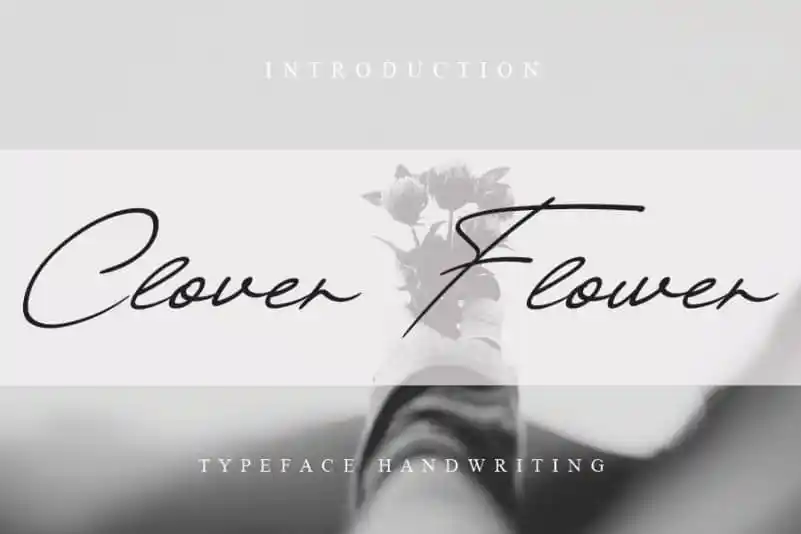
Clover Flower Handwritten Font – Download Grátis
A fonte ‘Clover Flower Handwritten Font’ é uma delícia para os olhos, sua textura suave e macia criando uma atmosfera harmoniosa e familiar. Perfeita para designers que valorizam elegância sem deixar de lado a simplicidade exuberante da escrita cursiva, esta fonte revigora qualquer projeto gráfico ao elevá-lo a um patamar inabalável de sofisticação e graça natural. Seja para criações de blogs pessoais, publicações online ou até mesmo para ilustrações em estilo vintage, ‘Clover Flower Handwritten Font’ é a escolha perfeita para aquelas pessoas que apreciam uma fonte que traz um toque suave e encantador ao seu trabalho. Seja você designer de interfaces de usuário, artista gráfico ou blogueira, esta fonte terá o poder de adicionar personalidade e elegância a seus projetos.